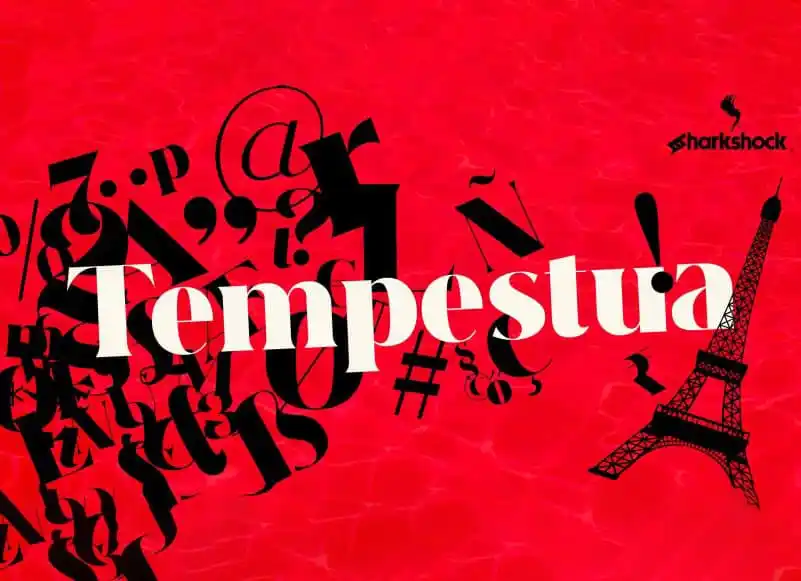
Tempestua Serif Font – Fonte Grátis
Tempestua Serif Font
A Tempestua Serif Font é uma tipografia serif que traz para a mesa um toque moderno através de seus ângulos afiados. Ideal para designers buscando uma harmonia entre elegância e agressividade, essa fonte oferece linhas finas com aparência leve apoiadas em linhas grossas, garantindo grande contraste. As letras minúsculas também apresentam suas sobrancelhas bem cortadas e tops de letra achatados, criando um movimento elegante que manterá os olhos flutuando pela página. Suas curvas elegantemente arredondadas prometem encantar qualquer leitor, fazendo-os pararem em sua lugar. Tempestua é perfeito para uso em logotipos de marcasluxuosos, capas de revistas e títulos de filmes. A versão completa da fonte inclui suporte ao alfabeto básico latino, a extensão latina/ diacriticos, calibragem e até mesmo o suporte para polonês.